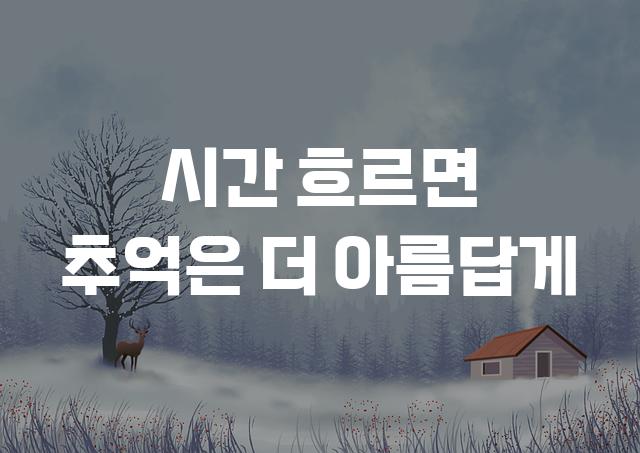
태백 은하수체는 현대적이면서도 부드러운 라인을 갖춘 둥근 고딕 폰트입니다. 이 폰트는 디지털 시대의 요구에 부응하면서도 따뜻하고 친근한 감성을 전달합니다.
태백 은하수체은(는)
기본 고딕, 둥근 스타일, 감성적인, 부드러움, 복실복실 계열의 생김새를 가지고 있으며
포스터, 초대장, 출판물 제목 등에서 자주 활용되며, 효과적인 메시지 전달에 적합합니다.
이 폰트는 출판/미디어, 문화/예술, 이벤트/웨딩 분야에 잘 어울리며,
감성적인, 예술적인, 클래식한 느낌을 담고 있는 것이 특징입니다.